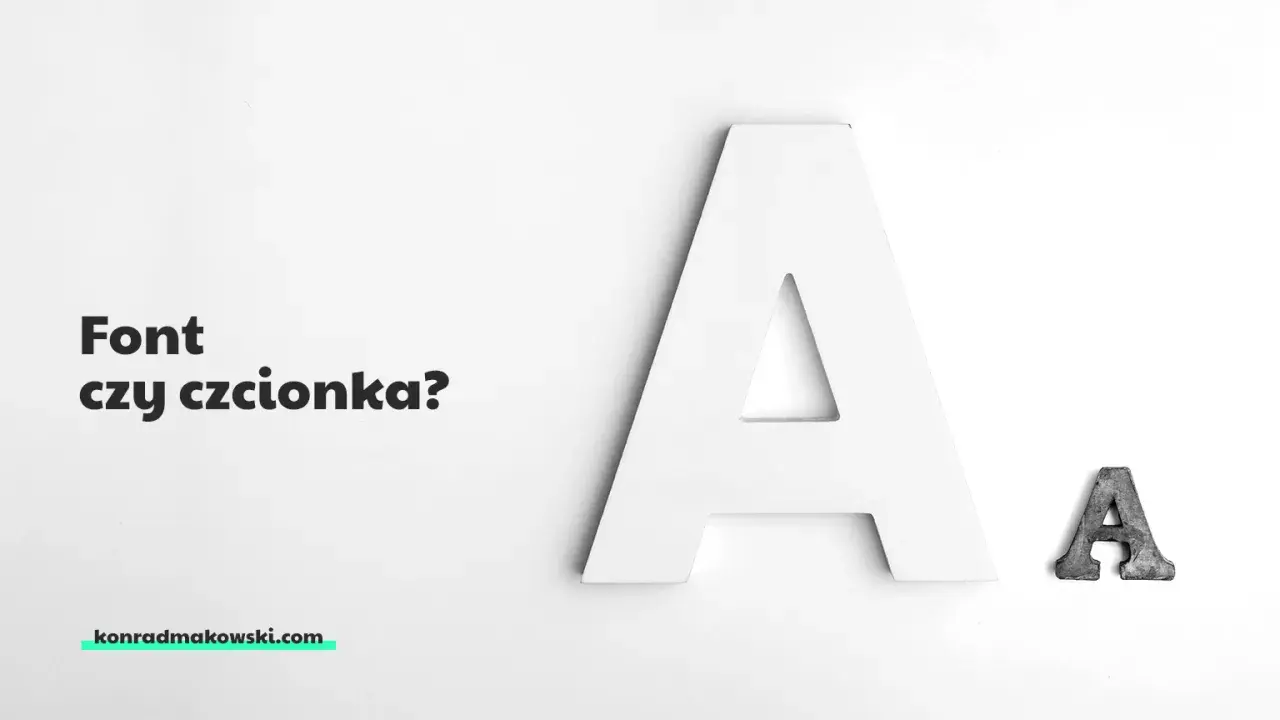
Najkrótsza odpowiedź i najważniejsza różnica
- Typeface to angielski termin najbliższy pojęciu kroju pisma.
- Font bywa używany jako nazwa konkretnej odmiany, pliku lub zestawu wariantów.
- W codziennej rozmowie te słowa często się mieszają, ale w typografii warto je rozdzielać.
- W briefie do grafika lepiej mówić o kroju, wadze, stylu i licencji niż o ogólnym „fontcie”.
- W materiałach marketingowych dla lokalnych firm liczy się nie tylko estetyka, ale przede wszystkim czytelność.
Najkrótsza odpowiedź brzmi tak
Jeśli potrzebujesz jednego terminu, najbliższym angielskim odpowiednikiem kroju pisma jest typeface. To słowo opisuje sam projekt liter: ich kształt, proporcje, charakter i spójność wizualną.
W praktyce wiele osób używa też słowa font, ale ono częściej odnosi się do konkretnej cyfrowej odmiany albo pliku z danym krojem. W codziennej rozmowie te pojęcia się mieszają, jednak w precyzyjnej typografii rozdzielam je od razu.
To ważne, bo dzięki temu łatwiej zamówić właściwy efekt: projekt kroju, pojedynczą odmianę albo pełną rodzinę. A to już prowadzi prosto do różnic, które najczęściej wywołują nieporozumienia.
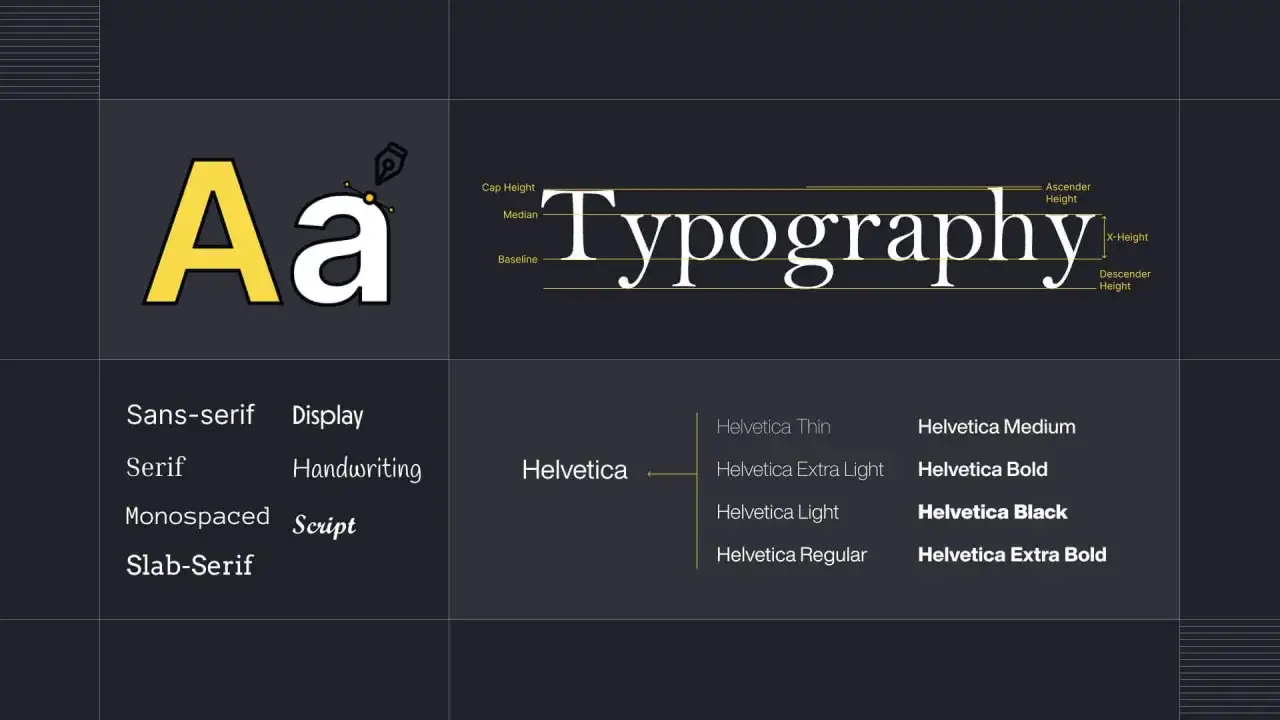
Czcionka, font i krój pisma nie są tym samym
To jeden z tych tematów, które w języku polskim przez lata się rozmyły. W praktyce warto myśleć o tym tak: krój pisma to projekt, a font to jego konkretna wersja albo plik używany w systemie.
| Termin | Najbliższy angielski odpowiednik | Co oznacza w praktyce | Przykład |
|---|---|---|---|
| Krój pisma | Typeface | Projekt liter jako całość | Helvetica jako rozpoznawalny projekt |
| Font | Font | Konkretna odmiana, styl lub plik | Helvetica Bold, Helvetica Italic |
| Rodzina kroju | Typeface family / font family | Zestaw spójnych odmian jednego projektu | Regular, Bold, Italic, Condensed |
| Czcionka | W mowie potocznej: font / typeface | Ogólne, nieprecyzyjne określenie | „Zmień czcionkę na stronie” |
Właśnie tu pojawia się typowy zgrzyt: ktoś prosi o „inną czcionkę”, a ma na myśli grubszą odmianę, większy kontrast albo po prostu lepszą czytelność. Gdy nazwiesz rzecz po imieniu, szybciej dostaniesz właściwy projekt zamiast kolejnej rundy poprawek.
Jeśli chcesz uniknąć niejasności, pamiętaj o prostym podziale: projekt liter, odmiana kroju i plik fontu to trzy różne poziomy. Gdy je rozdzielasz, łatwiej dobrać właściwe słowo do briefu, strony i druku.
Jak mówić precyzyjnie w briefie i na stronie
Najwięcej korzyści z tej wiedzy mam wtedy, gdy pracuję z klientem, grafikiem albo front-endowcem. Jedno zdanie z dobrym terminem często skraca rozmowę o połowę.
W rozmowie z grafikiem
Jeśli chcesz zmiany wyglądu liter, powiedz, że chodzi ci o inny krój pisma, grubszą odmianę albo większą czytelność. Lepiej działa zdanie: „Potrzebuję bezszeryfowego kroju do nagłówków” niż ogólne „zmień czcionkę”.
Warto też doprecyzować, czy potrzebujesz tylko jednej odmiany, czy całej rodziny z wersjami regular, bold i italic. To ma znaczenie, bo projekt może wyglądać podobnie w podglądzie, ale różnić się zakresem plików i licencji.Na stronie internetowej
W WWW liczy się nie tylko wygląd, lecz także format pliku i wydajność. Do internetu zwykle używa się formatów webowych, a do pracy lokalnej na komputerze innych plików. Dla czytelnika ważniejsze od nazwy jest to, czy tekst ładuje się szybko i pozostaje czytelny na różnych ekranach.
Tu dochodzi jeszcze jeden praktyczny detal: ten sam krój może działać dobrze jako nagłówek, ale już gorzej w dłuższym akapicie. Na ekranie liczą się światło między literami, wysokość x, ciężar linii i kontrast tła. To nie są ozdobniki dla profesjonalistów, tylko rzeczy, które decydują o komforcie czytania.
W druku i plikach przekazywanych do produkcji
Przy materiałach drukowanych trzeba sprawdzić licencję. Zdarza się, że font do projektu logo możesz kupić do użytku na komputerze, ale nie wolno ci osadzić go w serwisie albo przekazać go dalej do produkcji bez dodatkowych praw. To detal, który potrafi zatrzymać wdrożenie, gdy wszystko inne jest już gotowe.
Właśnie dlatego precyzja w słowie idzie tu w parze z precyzją w realizacji. A skoro to już uporządkowane, można przejść do najważniejszego pytania dla marketingu lokalnej firmy: co wybrać, żeby tekst naprawdę działał.
Jak dobrać krój do lokalnej marki
Tu patrzę mniej na modę, a bardziej na sytuację użycia. Inny efekt potrzebny jest na szyldzie przy ulicy, inny na ulotce do skrzynki, a jeszcze inny w kampanii social media.
- Szyld i witryna. Najważniejsza jest odległość od czytelnika. Sprawdzają się kroje o mocnej sylwetce, bez przesadnie cienkich linii i z wyraźnymi literami.
- Menu, cennik, oferta. Tu wygrywa prostota. Jeśli klient ma czytać szybko, lepiej ograniczyć ozdobniki i zostawić jedną wyraźną hierarchię nagłówków.
- Logo. Krój może być bardziej charakterystyczny, ale nie kosztem czytelności. Dobre logo nie musi krzyczeć, żeby zostało zapamiętane.
W marketingu lokalnym to ma realne znaczenie. Firma potrzebuje nie tylko ładnego wyglądu, ale też szybkiego odczytu, spójności z marką i materiałów, które da się użyć w druku, na stronie i w social media bez dodatkowych korekt.
Jeśli chcesz zapamiętać tylko jedno zdanie, niech będzie takie: „krój pisma” po angielsku to przede wszystkim „typeface”, a „font” warto zostawić na konkretną odmianę, plik albo potoczne użycie. To wystarczy, żeby mówić o typografii precyzyjniej i z większą pewnością, także wtedy, gdy przygotowujesz brief dla grafika albo opis materiałów reklamowych.